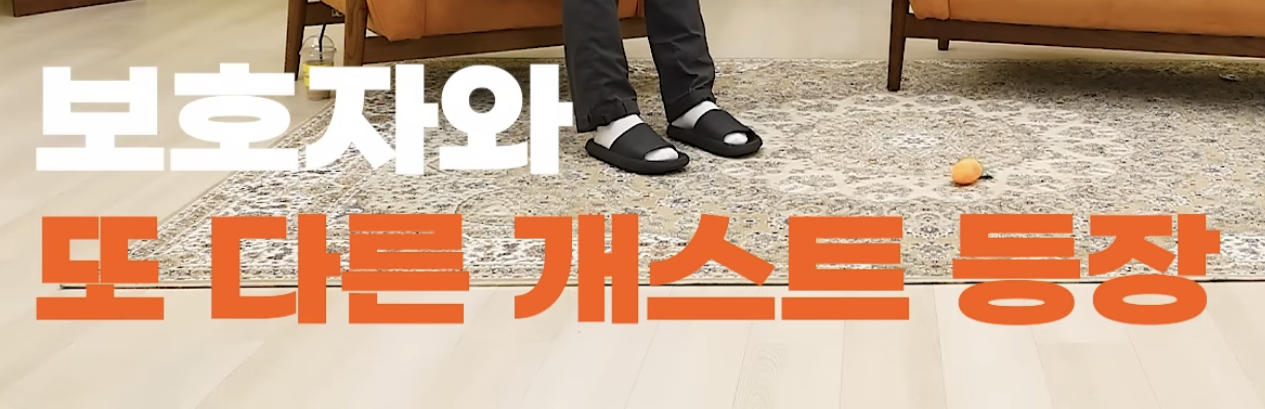
강형욱의 개스트쇼 자막 폰트
유튜브 강형욱의 개스트쇼 영상에 사용되는 폰트인데 예뻐서 대체 무슨 폰트인지 너무 궁금합니다 ㅜㅜ 산돌 검색도 해봤는데 못 찾았구요 G마켓 산스랑 비슷한 느낌인데 G마켓 산스보다는 납작하고 다른 폰트 같아서요 ㅠㅠ
G마켓 산스 Bold에 가로 장평값을 주면 비슷하게 나오네요.